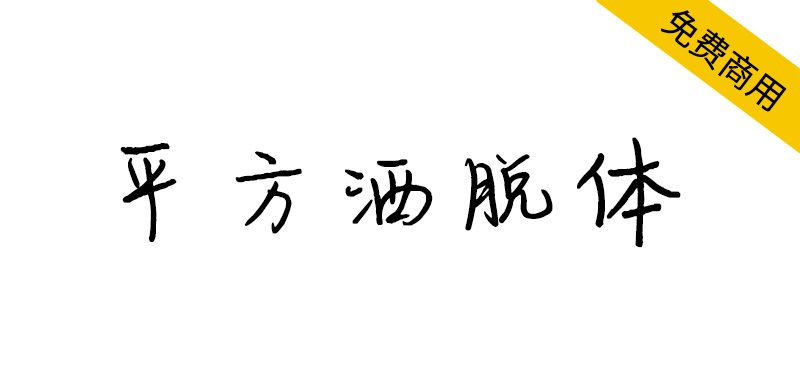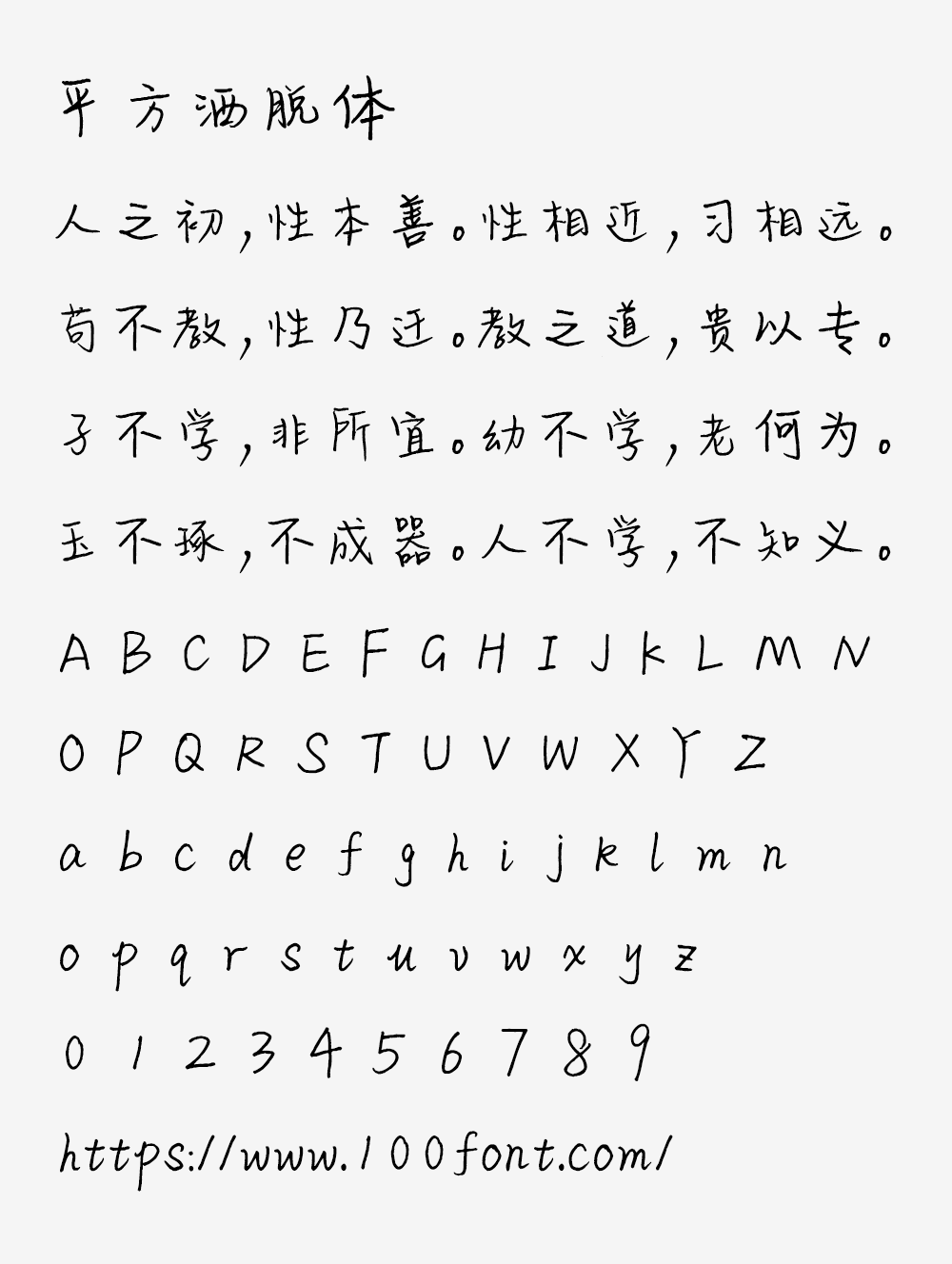
【平方洒脱体】一款飘逸潇洒的手写体字体
想要为你的设计注入一抹不羁的灵魂吗?这款「平方洒脱体」以灵动自然的笔触,将手写艺术的随性与专业设计的实用完美融合,线条飘逸却不失结构之美。更惊喜的是,它竟开放商业授权,个人和企业均可免费用于广告、电商、自媒体等多样场景!立即输入文字预览效果,解锁你的创意新风格。
【平方洒脱体】一款飘逸潇洒的手写体字体
平方洒脱体是一款兼具艺术性与实用性的手写风格字体,笔画粗细恰到好处,线条自然灵动,整体书写效果洒脱飘逸,可应用于各类飘逸潇洒的创意设计场景